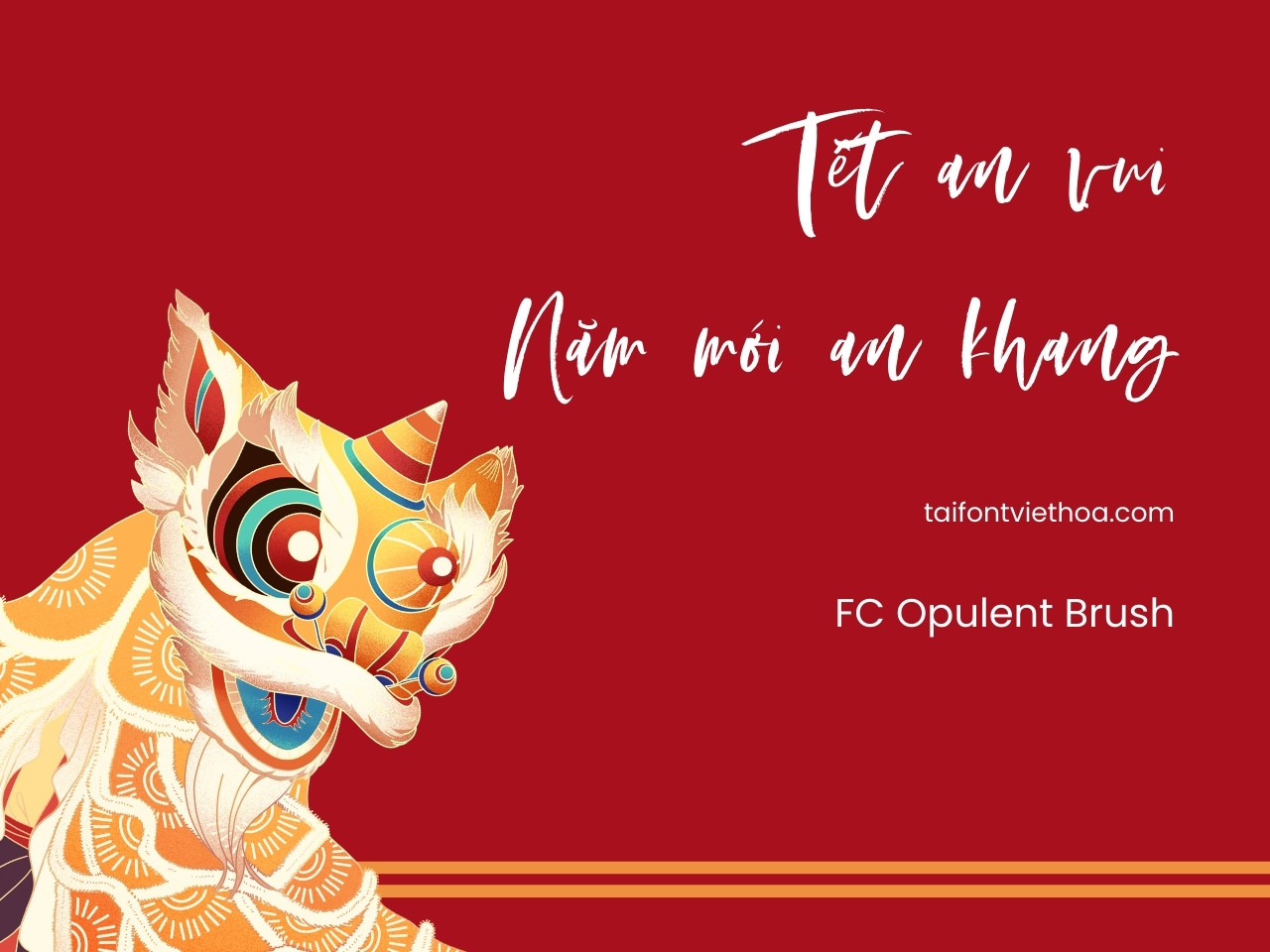
Font việt hóa FC Opulent Brush
Tác giả Font: Sam Parrett
Giới thiệu về font Opulent Brush và phiên bản Việt hóa
FC Opulent Brush là phiên bản Việt hóa từ font gốc “Opulent” – một phông chữ viết tay bằng cọ đầy nghệ thuật được thiết kế bởi Sam Parrett (nhà sáng lập Set Sail Studios – UK). Font ban đầu được phát hành trên nền tảng Creative Market và nhanh chóng được giới thiết kế yêu thích bởi sự pha trộn giữa nét tự nhiên của bút cọ và sự sang trọng, hiện đại trong từng đường nét. Opulent hỗ trợ hơn 70 ngôn ngữ dựa trên bảng mã Latin mở rộng, đồng thời đi kèm nhiều glyphs và stylistic alternates giúp mở rộng khả năng sáng tạo trong trình bày.
Phiên bản Việt hóa được cộng đồng Font Chuẩn thực hiện, bổ sung đầy đủ dấu tiếng Việt, giữ lại trọn vẹn tinh thần “cảm xúc thị giác” mà font gốc mang lại. Các ký tự được căn chỉnh lại cho phù hợp với thói quen đọc của người Việt nhưng không làm mất đi chất hoang dã, phóng khoáng vốn có. FC Opulent Brush đã được taifontviethoa.com sưu tầm, chọn lọc và đăng tải nhằm đáp ứng nhu cầu sáng tạo đa dạng cho cộng đồng thiết kế Việt Nam trong các dự án thực tế.
Đặc điểm thiết kế và ứng dụng thực tiễn
FC Opulent Brush sở hữu cấu trúc viết tay bay bổng với những đường cọ to bản, mềm mại nhưng cũng rất dứt khoát. Các ký tự có sự chuyển động tự nhiên, đậm chất thủ công, tạo nên cảm giác sống động, thân thiện và mang tính cá nhân hóa cao. Điểm nổi bật là các nét chữ không bị đóng khung trong quy tắc chuẩn, mang lại sự tự do cho thiết kế. Font này có sẵn các ký tự thay thế giúp người dùng biến tấu linh hoạt trong từng tiêu đề hoặc logo.
Opulent Brush rất phù hợp để dùng trong các thiết kế tiêu đề, typography quảng cáo, poster nghệ thuật, ấn phẩm thời trang, logo mang tính cá tính, hoặc các mẫu typography truyền cảm hứng trên mạng xã hội. Các ngành nghề lý tưởng để sử dụng font này gồm quảng cáo, mỹ phẩm, thời trang, ẩm thực, thiệp mời, và thiết kế cá nhân hóa cho blog hoặc social branding.